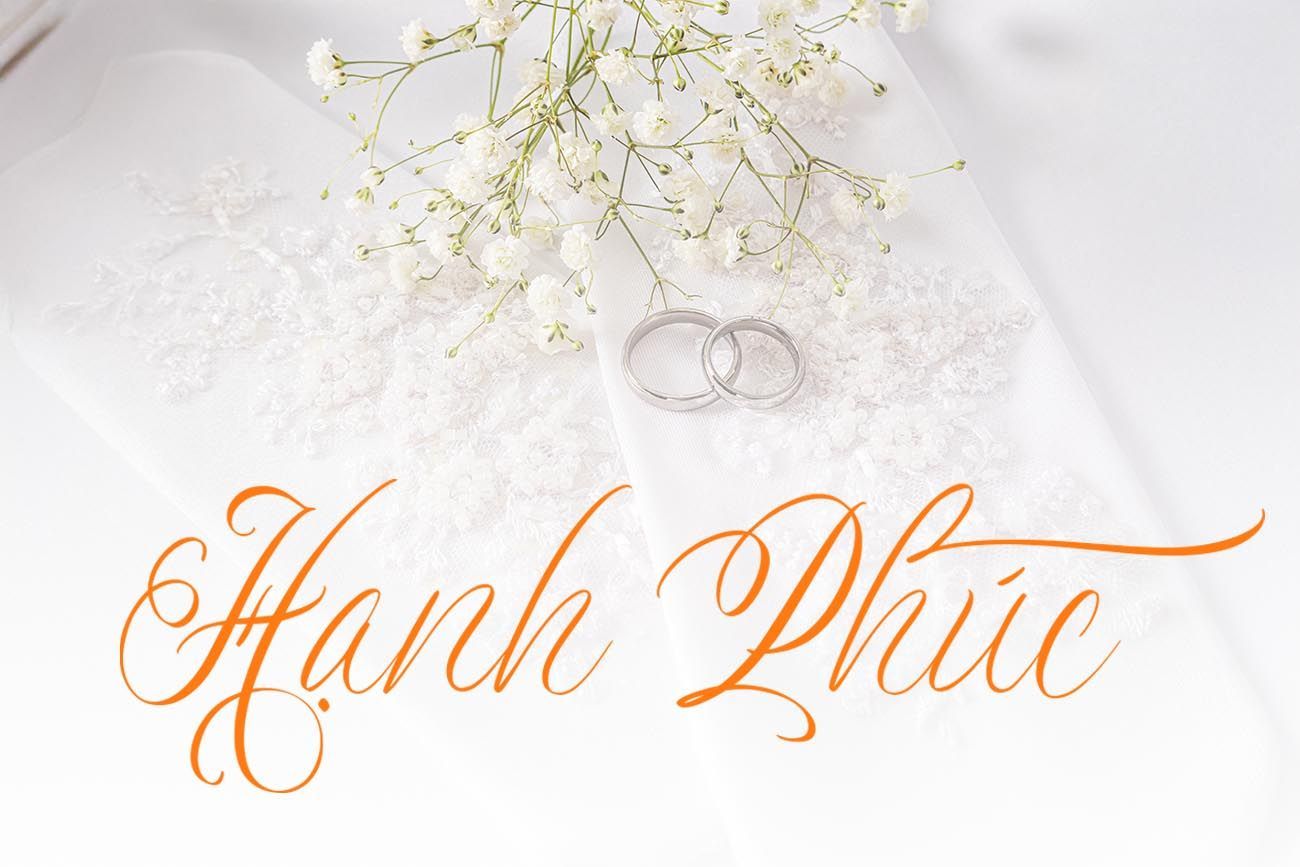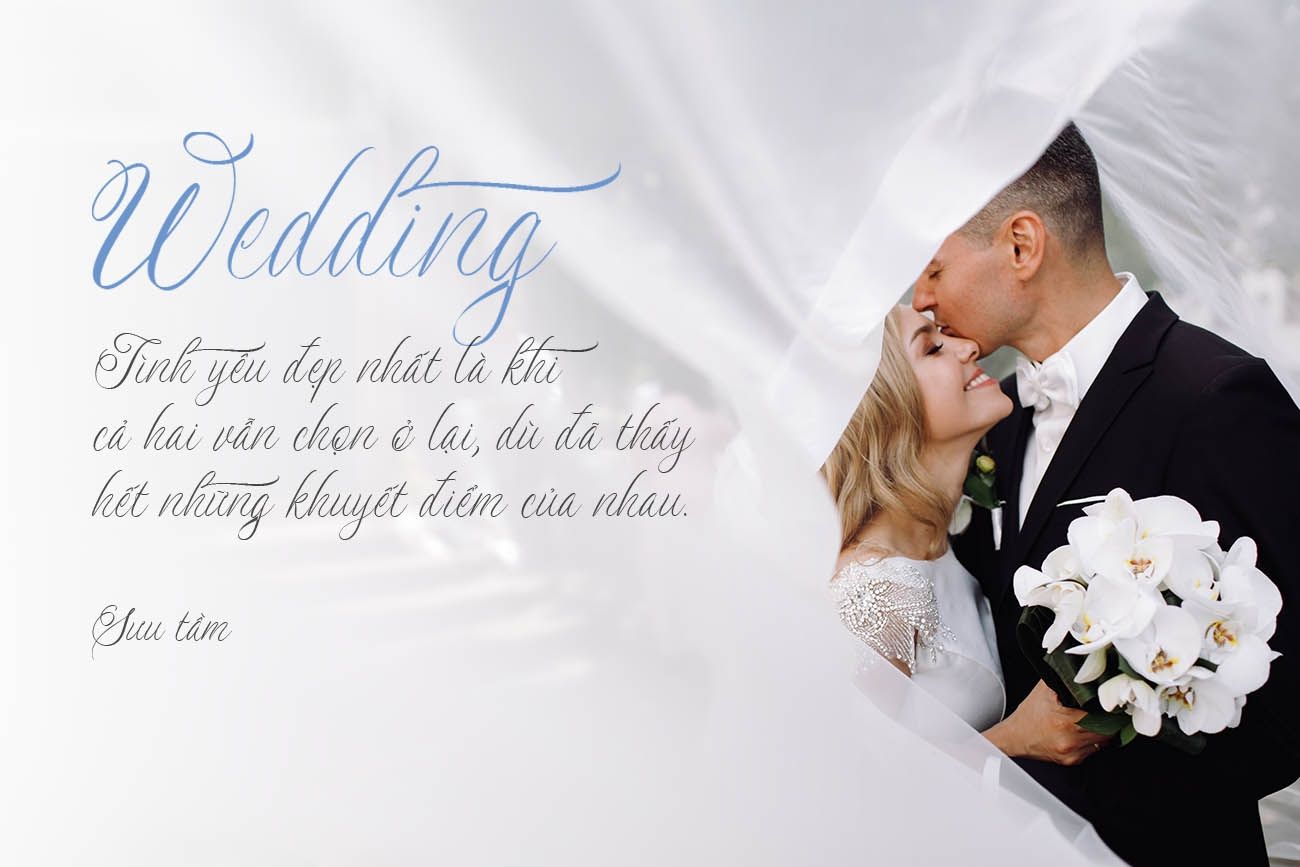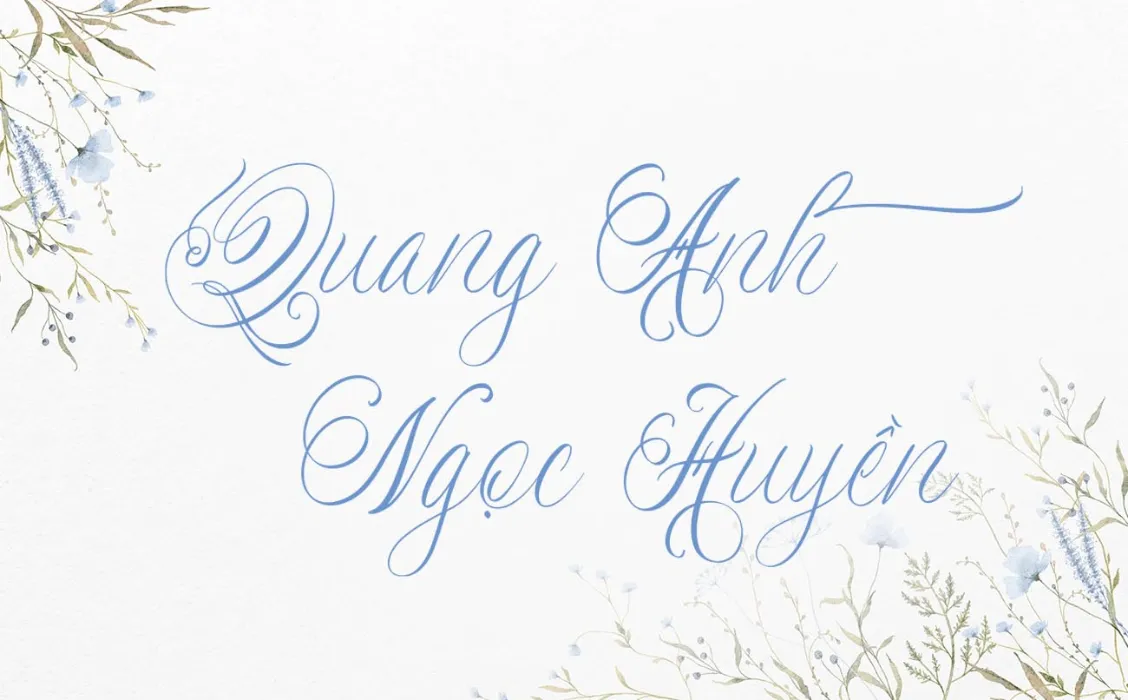
Mùa cưới là mùa của những khởi đầu ngọt ngào, nơi mỗi chi tiết nhỏ đều góp phần dệt nên câu chuyện tình yêu vĩnh cửu. Để giúp các cặp đôi ghi lại dấu ấn riêng biệt trong ngày trọng đại, TH Newly Bridal Việt hóa xuất hiện như một "nàng thơ" trong làng typography, mang đến vẻ đẹp tinh tế, sang trọng và đầy cảm xúc
TH Newly Bridal không đơn thuần là một phông chữ, mà là sự kết tinh của nghệ thuật thư pháp hiện đại. Với những nét mảnh mai xen lẫn các đường uốn lượn bay bổng, phông chữ này tái hiện lại cảm giác mềm mại như tà váy cưới hay những cánh hoa cầm tay rạng rỡ. Điểm đặc biệt nhất nằm ở bộ Glyphs (ký tự thay thế) đa dạng, cho phép người thiết kế tạo ra những điểm nhấn uốn lượn ở đầu và cuối chữ, giúp tên của cô dâu chú rể trở nên nổi bật và nghệ thuật hơn bao giờ hết.
Bản Việt hóa của phông chữ này đã được tinh chỉnh kỹ lưỡng, đảm bảo các dấu tiếng Việt hài hòa tuyệt đối với cấu trúc chữ mà không làm mất đi vẻ thanh thoát nguyên bản. Điều này giúp các cặp đôi tại Việt Nam dễ dàng ứng dụng vào nhiều hạng mục:
Thiệp cưới: Tạo ấn tượng đầu tiên sang trọng và chân thành đến khách mời.
Bảng Welcome & Menu: Tăng tính thẩm mỹ cho không gian tiệc cưới.
Album ảnh cưới: Ghi chú những mốc thời gian, lời thề nguyện đầy lãng mạn.
Ấn phẩm quà tặng: Mang lại sự chỉn chu và ấm áp trong từng món quà tri ân.
Giữa muôn vàn lựa chọn, TH Newly Bridal chính là "chìa khóa" mở ra không gian của sự thuần khiết và đẳng cấp. Hãy để mỗi dòng chữ viết ra đều trở thành một lời chúc phúc, một kỷ niệm đẹp khó phai trong mùa yêu thương này.